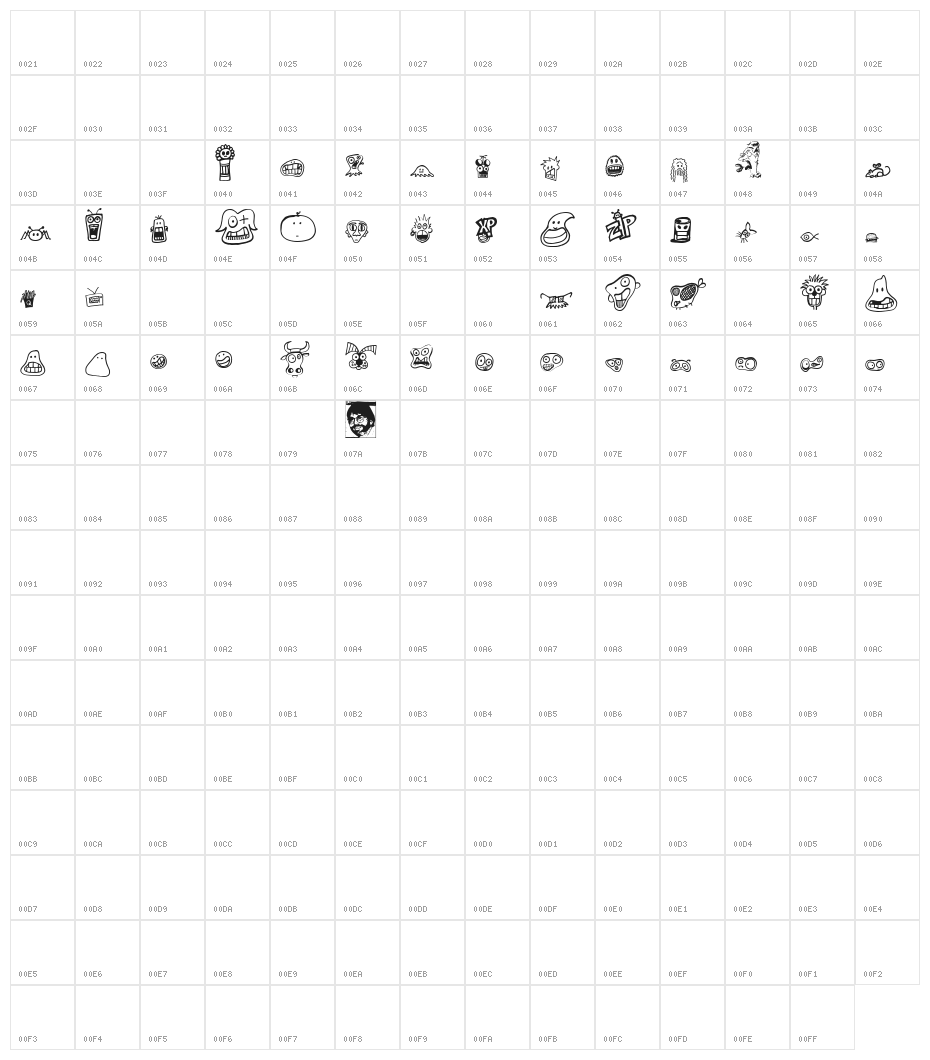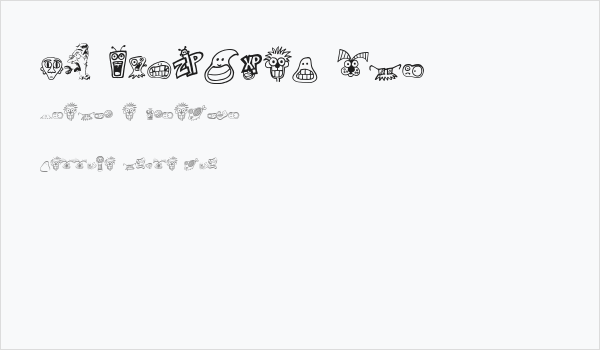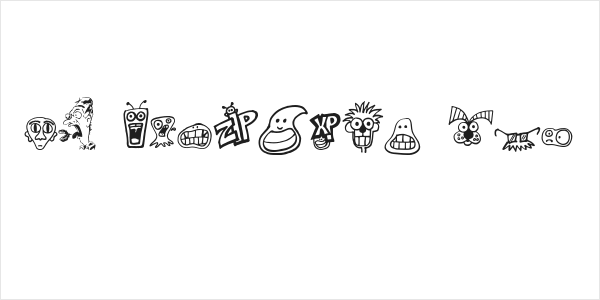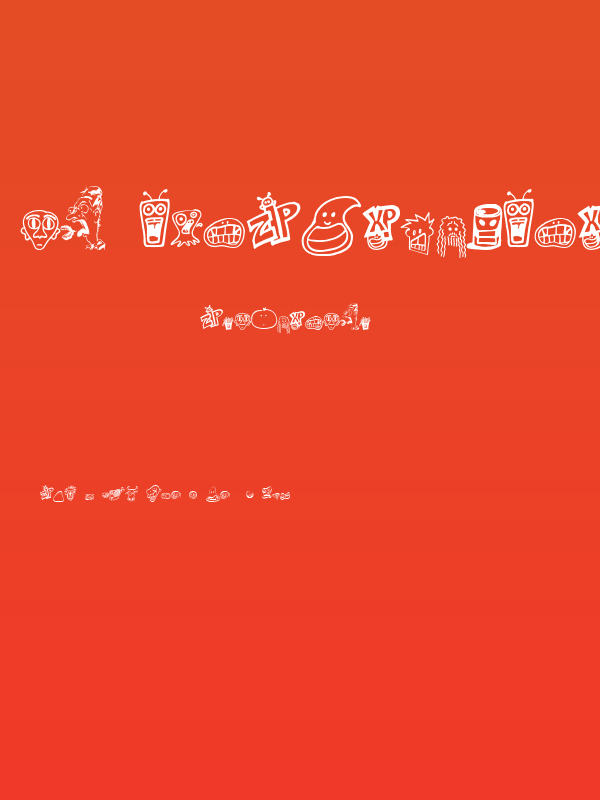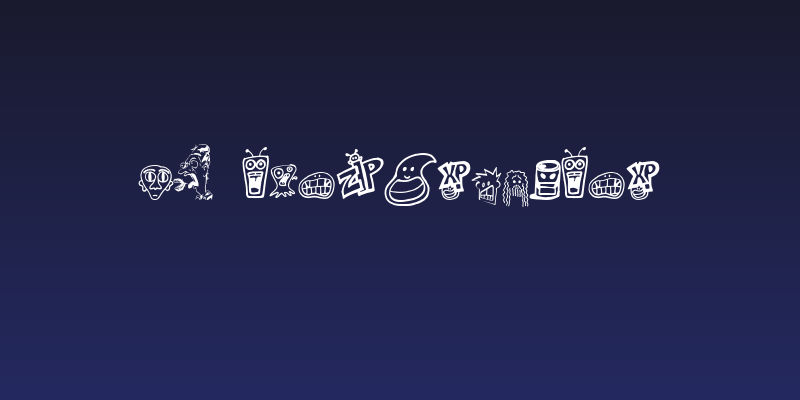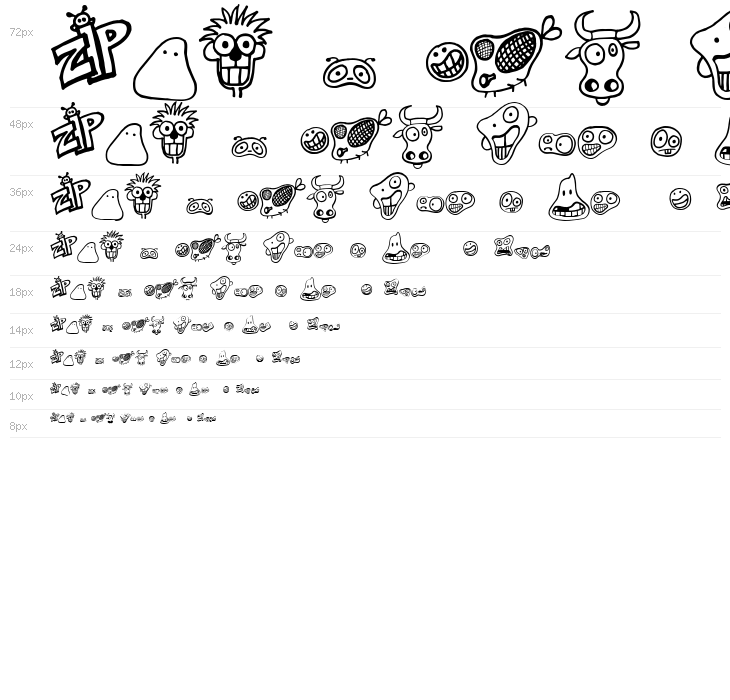
PHILBATSRegular Font
Diese Schriftart enthält 48 Zeichen. Klicken Sie auf ein Zeichen für Details.
| Kategorien | Dingbats |
| Gesamtstil | Playful and Artistic |
| Anwendungsfall | Logos, Posters, Artistic Projects |
| Vorgeschlagene Projekte | Ideal for children's books, comic strips, playful posters, and creative graphic design projects. |